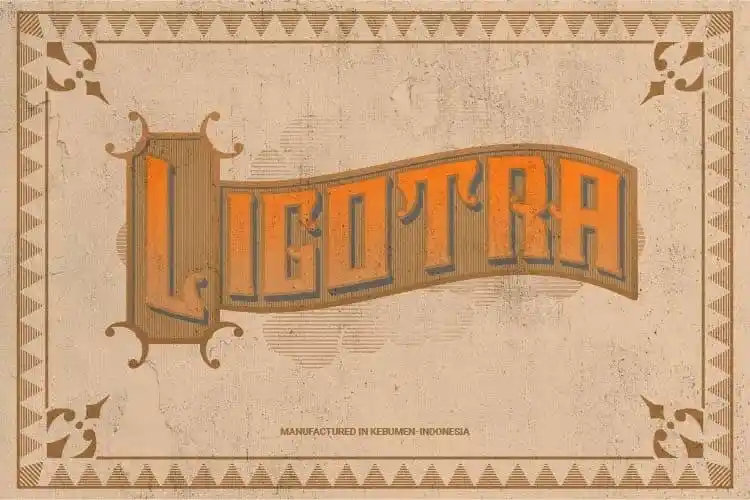
Ligotra Display Font – Download Grátis
Ligotra Display é uma fonte sans serif moderna com uma sensação de letra em caixa alta que se equilibra bem. Suas letras maiúsculas extensivas fornecem um amplo leque de opções criativas para os projetos gráficos. Foi desenvolvida pelo designer prioritype, cujo estilo vitoriano é simples e não muito complicado, mas ainda mantém um toque único. A fonte pode ser usada em uma variedade de cenários, desde headlines até elementos interativos de site ou materiais publicitários. Com sua grande gama de caracteres maiúsculos, você terá muitas alternativas para explorar e adaptar ao seu projeto específico. Ligotra Display é a escolha perfeita para quem busca um estilo moderno, versátil e charmoso sem comprometer a simplicidade. Experimente agora e encontre suas possibilidades criativas!